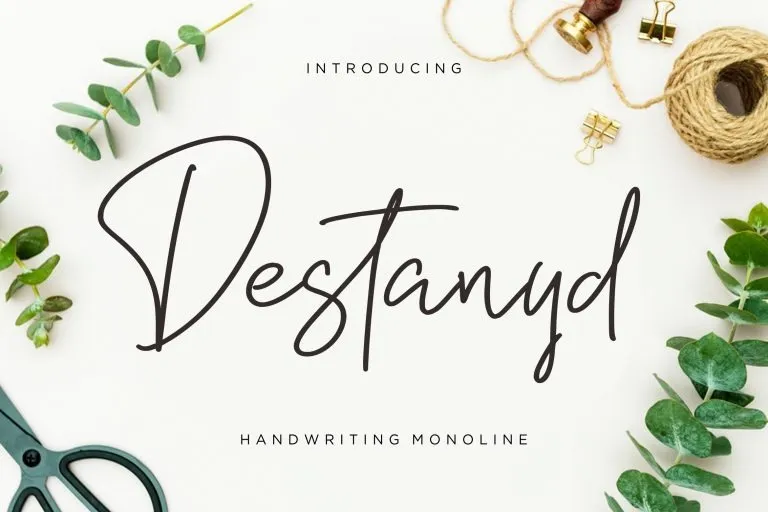
A ‘Destanyd Font’ é uma elegante tipografia escrita a mão criada pelo Designer Creatype Studio. Suaviza qualquer projeto com sua natureza encantadora, perfeita para trabalhos de design casual que desejam dar um toque familiar e confortável aos seus projetos. Essa fonte é perfeita para aqueles momentos em que você quer adicionar uma pitada de casualidade ao seu trabalho de design sem comprometer sua aparência elegante. Seja para o texto interno de seu site, o conteúdo de suas redes sociais ou até mesmo os títulos dos seus produtos, a ‘Destanyd Font’ é uma escolha ótima para designers buscando personalizar e humanizar seus designs de forma única e sofisticada.